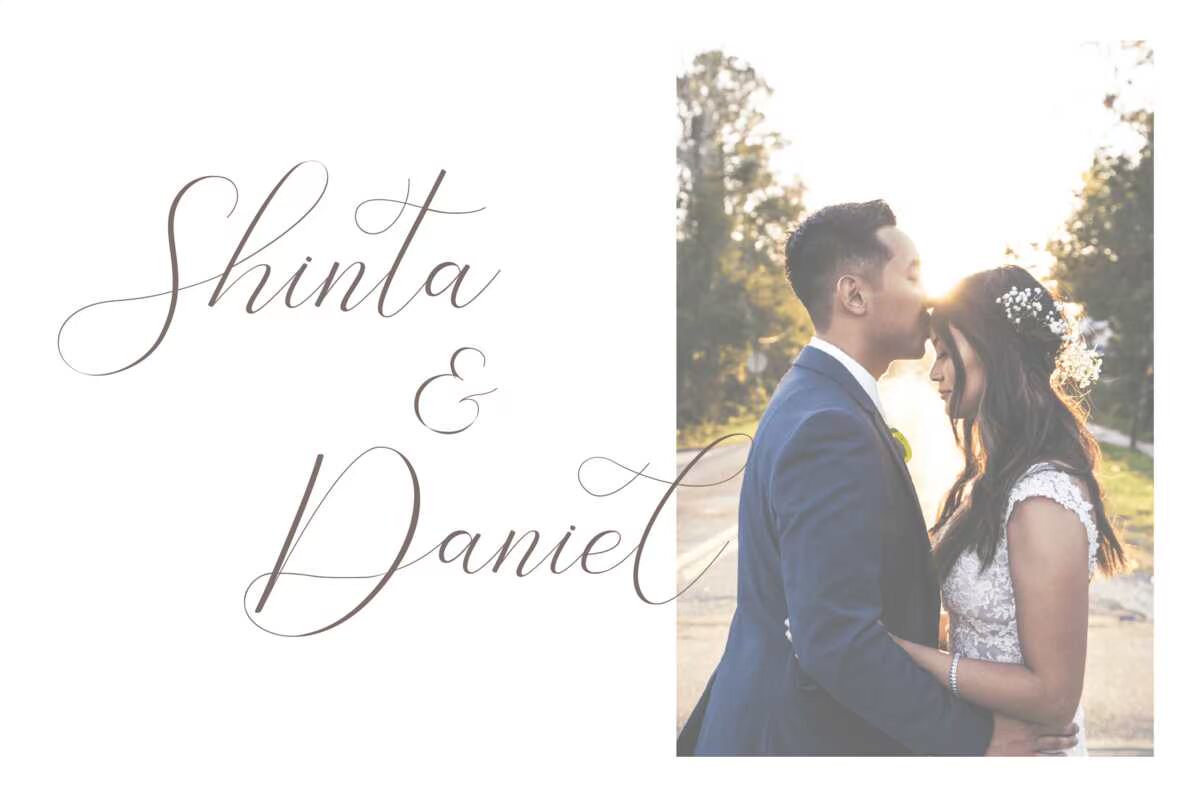
介绍Bathery CaligraphyFont。这款Font非常适合您的需要。这款Font配有大写字母、小写字母、标点符号、数字、漂亮的字母、优雅的连字和多语言支持。这款Font适用于各种需求,如徽标设计/品牌、水印照片、产品包装、,还有更多。介绍Bathery CaligraphyFont。这款Font非常适合您的需要。这款Font配有大写字母、小写字母、标点符号、数字、漂亮的替换字、优雅的连字和多语言支持。这款Font适用于各种需求,如商标设计/品牌、水印照片、产品包装等。